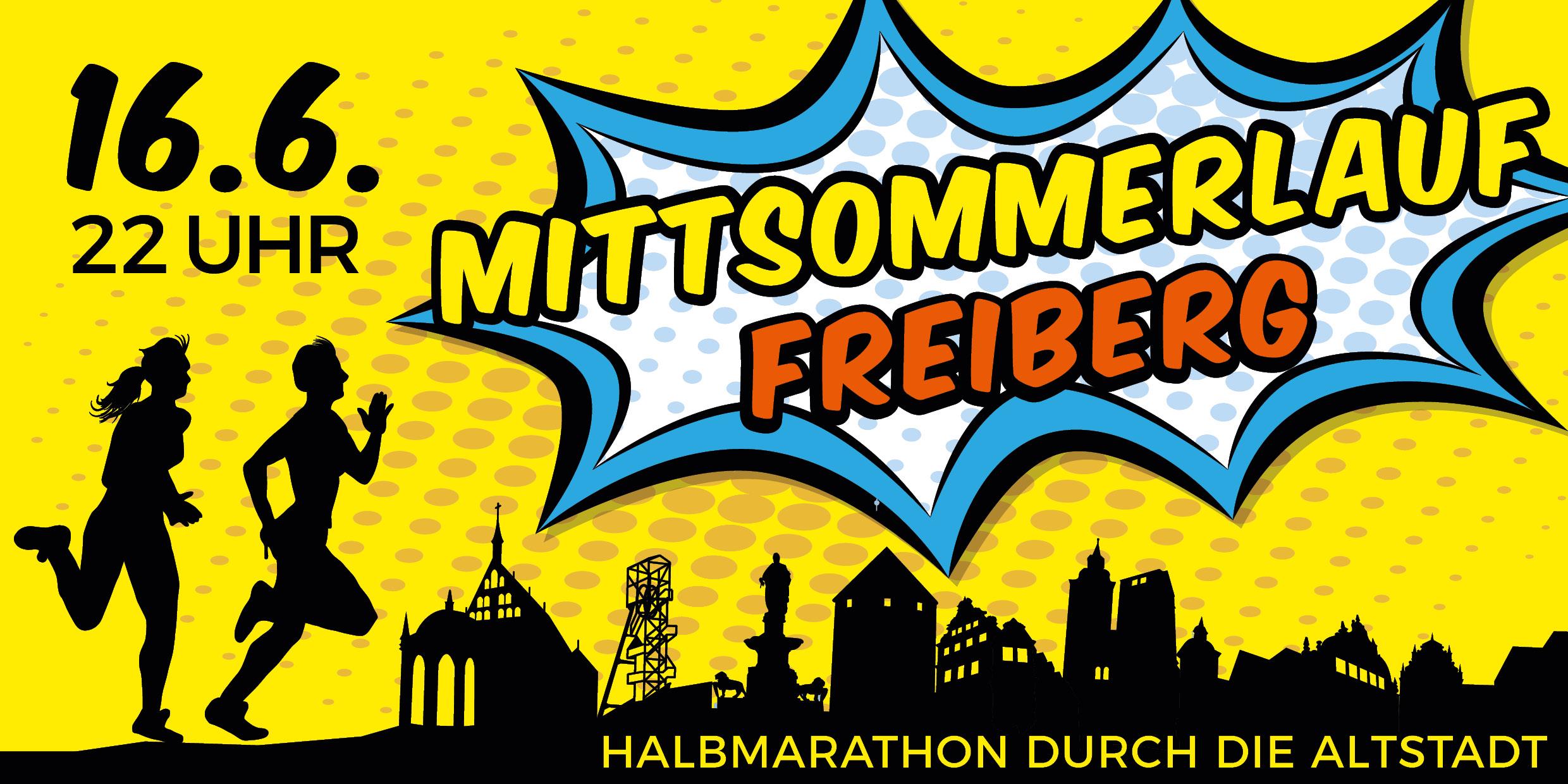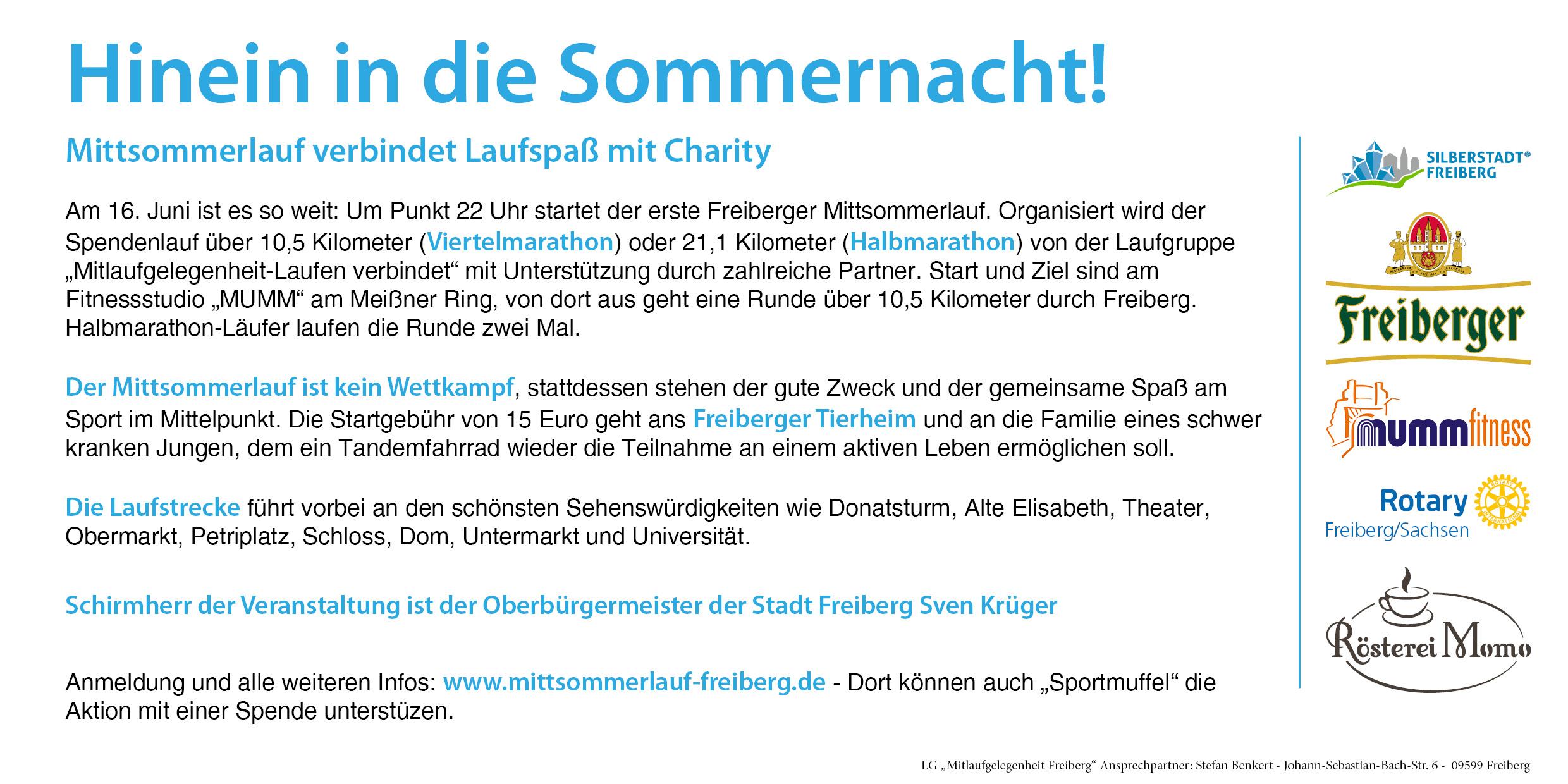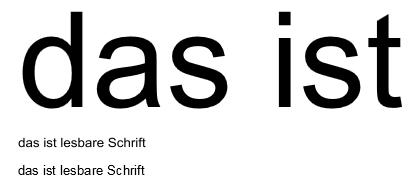
Schrift Midsummer Half
Aber sicher. Das Hinting wirkt sich bei niedrigen Auflösungen doch ganz anders auf die Darstellung aus. Und hier geht es gerade um eine sehr niedrige Auflösung.
Nein. Das Hinting beschreibt lediglich, wie ein Buchstabe auf einem niedrig aufgelösten Monitor dargestellt wird, solange der Buchstabe noch als Font vorliegt.
Hinting hat aber nichts damit zu tun, wie ein Buchstabe gerastert wird, wenn aus dem Vektorformat ein Pixelformat wird. Es wird beim Rastern  als Bild überhaupt nicht berücksichtigt, auf welchem Monitor das Pixelbild später dargestellt wird. Wie auch?
Ich rate dazu, beides auszuprobieren, wenn einem ein Bild wirklich wichtig ist, also zu experimentieren und zu vergleichen.
Reinzeichnung hat nichts mit experimentieren zu tun, da liegst du völlig daneben. Du kannst das aber für dich gern halten wie du möchtest.
Jetzt aber mal zurück zum Thema.
Das Hinting beschreibt lediglich, wie ein Buchstabe auf einem niedrig aufgelösten Monitor dargestellt wird, solange der Buchstabe noch als Font vorliegt.
Das Hinting greift abhängig von der absoluten Auflösung, nicht von der relativen.
Endlich hast du es verstanden.
Dass du beratungsresistent bist, oder was? Das ist auch keine Neuigkeit.
Es ist doch so, dass das Hinting allein bei der Ausgabe des ungerasterten Fonts auf dem Monitor zum Tragen kommt. Das Rastern in der Ausgabeauflösung als Bild hat mit dem Hinting doch gar nichts zu tun.
Darum mache ich das oft so, das ich den Text gar nicht im Grafikprogramm mache, sondern in der Textverarbeitung, dfamit die kompletten Textfunktionen zum tragen kommen, also Hinting, Kerning, OpenType-Funktionen, und davon in der Zielgröße einen Schreenshot mache. Diesen Text dann in die auf Fertigmaß skalierte Grafik einfüge.
Ich habe in Einzelfällen auch schon Screenshots von in Office dargestelltem Text gemacht und die dann in Photoshop-Ebenen gelegt, weil die Kantenglättung besser war als mit Photoshops Algorithmen. Oder Textebenen kopiert und die Deckkraft einer der Ebenen reduziert und damit das Ergebnis verbessert.
Der Punkt ist, dass man sich bei geringen Auflösungen nicht blind darauf verlassen kann, was Photoshop mit dem Text macht. Und erst zu rastern und dann zu verkleinern ist eine Option, mit der sich manchmal bessere Ergebnisse erzielen lassen, aber keine Regel. Mehr habe ich zu keinem Zeitpunkt geschrieben.
Mit der Vorlage geht es jetzt an die anderen Werbeartikel :-)  Für den Flyer haben wir einfach den fertigen Banner genutzt und dazu diese Rückseite ...
"Mitlaufgelegenheit – Laufen verbindet" müsste das geschrieben werden, also mit zwei Leerzeichen und Gedankenstrich statt Bindestrich.
Interessant aber für mich alles eine Nummer zu hoch. Ich komme da leider nicht mit ...
Vereinfacht: Computerschriften sind heutzutage in der Regel Schriften, die aus mathematischen Kurvenbeschreibungen bestehen. Bei der Darstellung auf dem Bildschirm oder beim Drucken werden die Linien bzw. Kurven, aus denen der Buchstabe besteht, dann aber nicht als durchgehende Linien, sondern als Zusammensetzung von lauter einzelnen Punkten gezeichnet (Ausnahme Plotter), wobei ein Punkt auf dem Monitor dicker ist als ein Punkt auf dem Laser oder in der Druckmaschine. Dünner als ein Punkt geht nicht. Eine Linie, die auf dem Bildschirm eigentlich zweieinhalb Punkte dick sein müsste, kann aber natürlich nur mit entweder zwei oder mit drei Punkten dargestellt werden, Wenn also ein »n« zufällig so auf dem Bildschirm steht, das beim vorderen Bein ab- und beim hinteren Bein aufgerundet wird, dann sieht das blöd aus, weil beide Beine eigentlich gleich dick sein sollten. Um das zu vermeiden, werden »Hinting«-Informationen in eine Schrift eingebaut, die dem Computer sagen, dass beispielsweise die zwei Beine vom n immer gleich dick bleiben sollen.
Dieses Hinting greift natürlich nicht mehr, wenn man das Bild mit der Schrift als Grafik speichert, weil die Schrift dann ja mit dem Rest vom Bild in ein Punktmuster gewandelt wird und also keine Schrift mehr ist. Da werden beim Verkleinern oder Vergrößern alle Bildpunkte gleichmäßig vermehrt oder reduziert. Und Arno hat nun gemeint, dass es manchmal ein besseres Ergebnis bringen könnte, wenn man vor der Umwandlung von Text zu Bild mit verschiedenen Skalierungsstufen ausprobiert, wie sich da das Hinting auswirkt, sodass dann für die Umwandlung in ein Punktmuster bessere Voraussetzungen gegeben sind.
Und jetzt darfst Du die Diskussion zwischen Bertel und Arno nochmal lesen …
Und wenn ich eine Schrift in der endgültigen Zielgröße mit einer Textverarbeitungf oder einem DTP-Progamm verwencde, dann wird eben auf diese Schrift sowohl das Hinting, als auch das Kerning pasasend zu dieser Schriftgröße angewendet. der Text ist dann eigentlich optimal auch in derGröße, wi der Text nur ein paar Pixel hoch  ist. Mache ich davon dann einen Screenschot und baue das mit entsprechenden Filteroptionen in das Pixelbild ein, bekomme ich einen gut lesbaren Text in der Grafik.
Erstelle ich aber die Grafik zunächst mit extrem größerer Auflösung, und habe dann in der Größe wirkklich schön sauberen Text, der in dieser Auflösung die Hilfe durch das Hinting gar nicht benötigt, sieht das erst einmal gut aus. Verkleinewre ich dann aber die Auflösung, werden aber die Ausgangspixel die in der Zielgröße dann auf einem Pixel landen vermischt, das Pixel bekommt dann einen Durchschnittsswert aller dieser Ausgangspixel berechnet.
Zum Thema Spende: ich wüßte schon gerne, wer da bespendet wird. Bei bestimmten Einrichtungen würde ich lieber nicht mitlaufen, als denen einen Teil meiner Startgebühr zu spenden.
Auf jeden Fall. Die Frage ist, ob es als Info auf das Plakat muss. Auf der Website steht es ja dann ausführlich beschrieben.